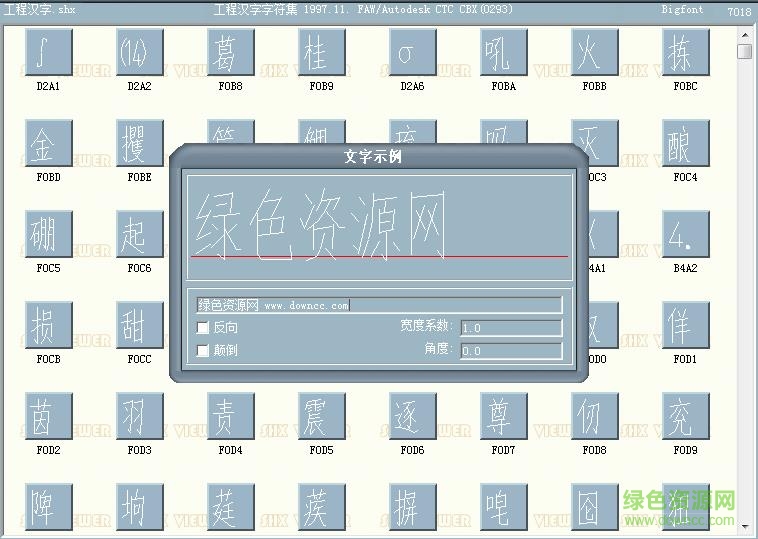
工程漢字.shx字體是在眾多工程制作中需要進(jìn)行調(diào)用的漢子字體,這些字體擁有工程制圖中所規(guī)定的各類標(biāo)準(zhǔn)能夠完美的進(jìn)行調(diào)用,完成各類規(guī)定的圖紙效果,快來綠色資源網(wǎng)下載吧!
工程漢字.shx內(nèi)的字體都為工程制圖中所需的漢字字體,將漢字的各類風(fēng)格進(jìn)行了工程制圖風(fēng)格修改,能夠帶給用戶最標(biāo)準(zhǔn)的工程制圖成品圖。